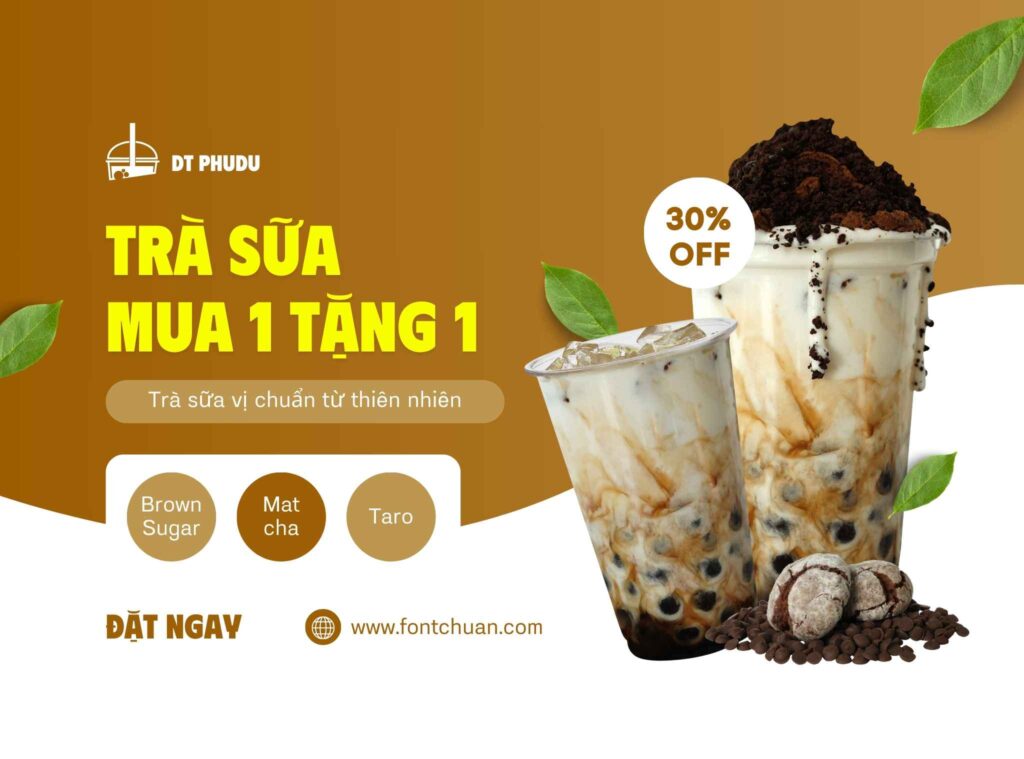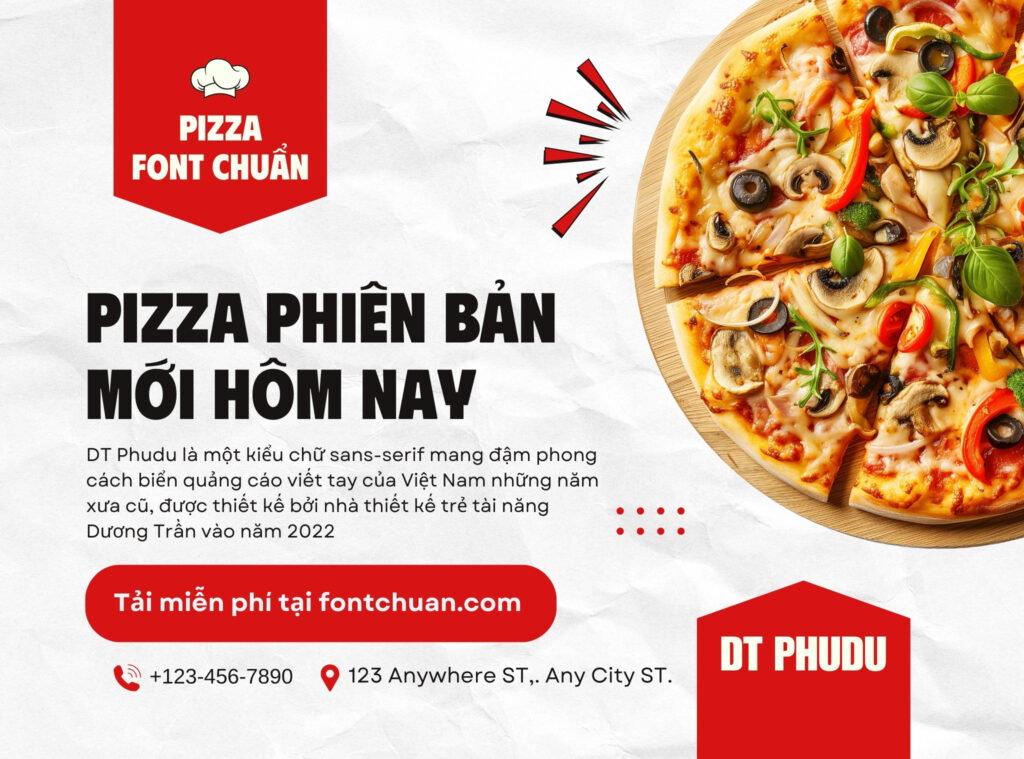
DT Phudu là một kiểu chữ sans-serif mang đậm phong cách biển quảng cáo viết tay của Việt Nam những năm xưa cũ, được thiết kế bởi nhà thiết kế trẻ tài năng Dương Trần vào năm 2022. Font này là sự kết hợp giữa nét hoài niệm và tinh thần hiện đại, thể hiện qua từng đường nét chắc khỏe nhưng vẫn giữ được độ mềm mại đặc trưng của bảng hiệu vẽ tay. Với phong cách rõ ràng, cá tính nhưng gần gũi, DT Phudu trở thành lựa chọn lý tưởng cho những thiết kế cần chất riêng, đậm chất Việt. Ngoài ra, DT Phudu cũng có thể sử dụng như một Font chữ Giáng Sinh, lý tưởng để trang trí thiệp, poster hay banner mùa lễ hội, mang đến không khí vui tươi, ấm áp và rộn ràng cho các sản phẩm thiết kế.
Bộ Font DT Phudu Việt Hóa mới nhất được thành viên Font Chuẩn đăng tải, mặc định đã hỗ trợ hơn 190 ngôn ngữ, trong đó bao gồm đầy đủ các ký tự tiếng Việt có dấu. Font không cần qua quá trình Việt hóa riêng vì đã được chính tác giả phát triển với mục tiêu phục vụ cộng đồng thiết kế trong nước. Nhờ khả năng tương thích cao, người dùng có thể dễ dàng áp dụng trong nhiều môi trường thiết kế, kể cả khi làm việc đa ngôn ngữ hoặc thiết kế cho thị trường quốc tế có yếu tố Việt.
Về đặc điểm thiết kế, DT Phudu sở hữu cấu trúc sans-serif khỏe khoắn, với các nét chữ được điều chỉnh tinh tế để mô phỏng cảm giác bảng hiệu vẽ tay. Font gồm 5 trọng số từ Light đến Black, cho phép linh hoạt khi sử dụng cho tiêu đề lớn, nhấn mạnh nội dung hoặc thiết kế mang tính nhận diện thương hiệu. Đây là lựa chọn tối ưu cho các dự án thiết kế như biển hiệu nhà hàng, poster retro, logo sáng tạo, menu quán ăn, thiết kế ngành ẩm thực hoặc thương hiệu gắn với yếu tố truyền thống.